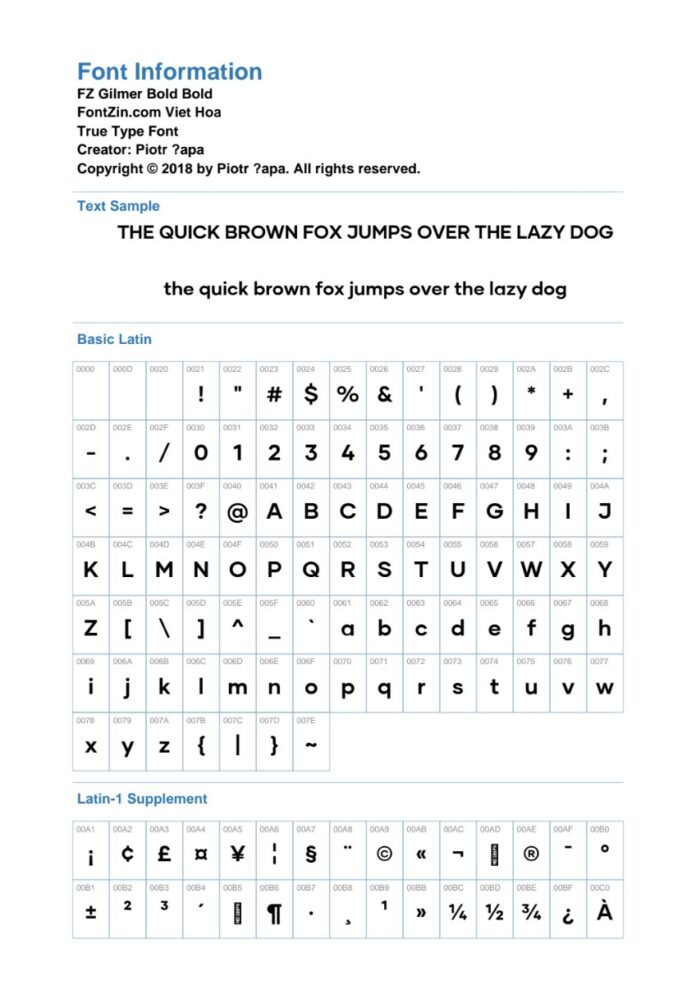
Trong thế giới thiết kế đồ họa đầy cạnh tranh, việc lựa chọn một bộ font chữ phù hợp có thể tạo nên sự khác biệt lớn cho tác phẩm của bạn. Font Gilmer Bold là một trong những lựa chọn hàng đầu được các nhà thiết kế chuyên nghiệp tin dùng nhờ vào vẻ đẹp hiện đại, mạnh mẽ và tính ứng dụng cao. Đặc biệt, phiên bản Việt Hóa của font này càng trở nên giá trị hơn, giúp các nhà thiết kế tại Việt Nam dễ dàng tạo ra những ấn phẩm chất lượng mà không gặp rào cản về ngôn ngữ.
Giới thiệu về Font Gilmer Bold
Gilmer Bold là một font chữ sans-serif hiện đại, được thiết kế với các đường nét rõ ràng, mạnh mẽ và cân đối. Font này nổi bật với sự đơn giản nhưng tinh tế, mang lại cảm giác chuyên nghiệp và hiện đại cho bất kỳ dự án nào. Ban đầu, Gilmer Bold được tạo ra bởi Piotr Łapa, một nhà thiết kế tài năng, và nhanh chóng trở thành một trong những font được yêu thích trong cộng đồng thiết kế toàn cầu. Với các ký tự được thiết kế tỉ mỉ, Gilmer Bold không chỉ dễ đọc mà còn có khả năng thu hút sự chú ý, làm cho nó trở thành lựa chọn lý tưởng cho tiêu đề, logo, poster và nhiều ứng dụng khác.
Đặc điểm nổi bật của Font Gilmer Bold
- Thiết kế hiện đại: Các đường nét hình học rõ ràng, mang lại vẻ đẹp đương đại và tối giản.
- Độ đọc cao: Dù là chữ hoa hay chữ thường, các ký tự đều được tối ưu để dễ đọc ở nhiều kích thước khác nhau.
- Tính linh hoạt: Phù hợp với nhiều loại hình thiết kế, từ in ấn đến kỹ thuật số, từ branding đến editorial.
- Phong cách mạnh mẽ: Phiên bản Bold đặc biệt tạo ấn tượng mạnh mẽ, rất thích hợp cho các thông điệp cần sự nổi bật.
Font Gilmer Bold Việt Hóa – Lợi ích và ứng dụng
Việc Việt Hóa Font Gilmer Bold mang lại nhiều lợi ích to lớn cho cộng đồng thiết kế Việt Nam. Một bộ font được Việt Hóa hoàn chỉnh sẽ bao gồm đầy đủ các ký tự tiếng Việt có dấu, giúp các nhà thiết kế không còn phải lo lắng về việc thiếu ký tự hay lỗi hiển thị khi sử dụng font chữ quốc tế. Điều này không chỉ tiết kiệm thời gian mà còn đảm bảo tính chuyên nghiệp và thẩm mỹ cho các sản phẩm thiết kế.
Lợi ích khi sử dụng Font Gilmer Bold Việt Hóa
- Đầy đủ ký tự tiếng Việt: Hỗ trợ tất cả các dấu tiếng Việt, đảm bảo văn bản hiển thị chính xác và đẹp mắt.
- Tăng tính chuyên nghiệp: Giúp các ấn phẩm thiết kế mang đậm bản sắc Việt mà vẫn giữ được phong cách hiện đại của font gốc.
- Tiết kiệm thời gian: Không cần chỉnh sửa thủ công các ký tự bị lỗi, giúp quy trình làm việc nhanh chóng và hiệu quả hơn.
- Tăng cường khả năng tiếp cận: Dễ dàng tạo ra nội dung phù hợp với đối tượng người dùng Việt Nam.
Ứng dụng đa dạng trong thiết kế
Font Gilmer Bold Việt Hóa có thể được ứng dụng trong rất nhiều lĩnh vực thiết kế khác nhau:
- Thiết kế logo và branding: Tạo ra các logo mạnh mẽ, hiện đại và dễ nhận diện cho các thương hiệu.
- Thiết kế poster và banner: Giúp các tiêu đề quảng cáo nổi bật, thu hút sự chú ý của người xem.
- Thiết kế website và ứng dụng di động: Đảm bảo trải nghiệm đọc tốt cho người dùng với giao diện sạch sẽ, hiện đại.
- Thiết kế sách, tạp chí và ấn phẩm in ấn: Mang lại vẻ đẹp chuyên nghiệp và dễ đọc cho nội dung.
- Thiết kế bao bì sản phẩm: Tạo ấn tượng mạnh mẽ và sang trọng cho các sản phẩm.